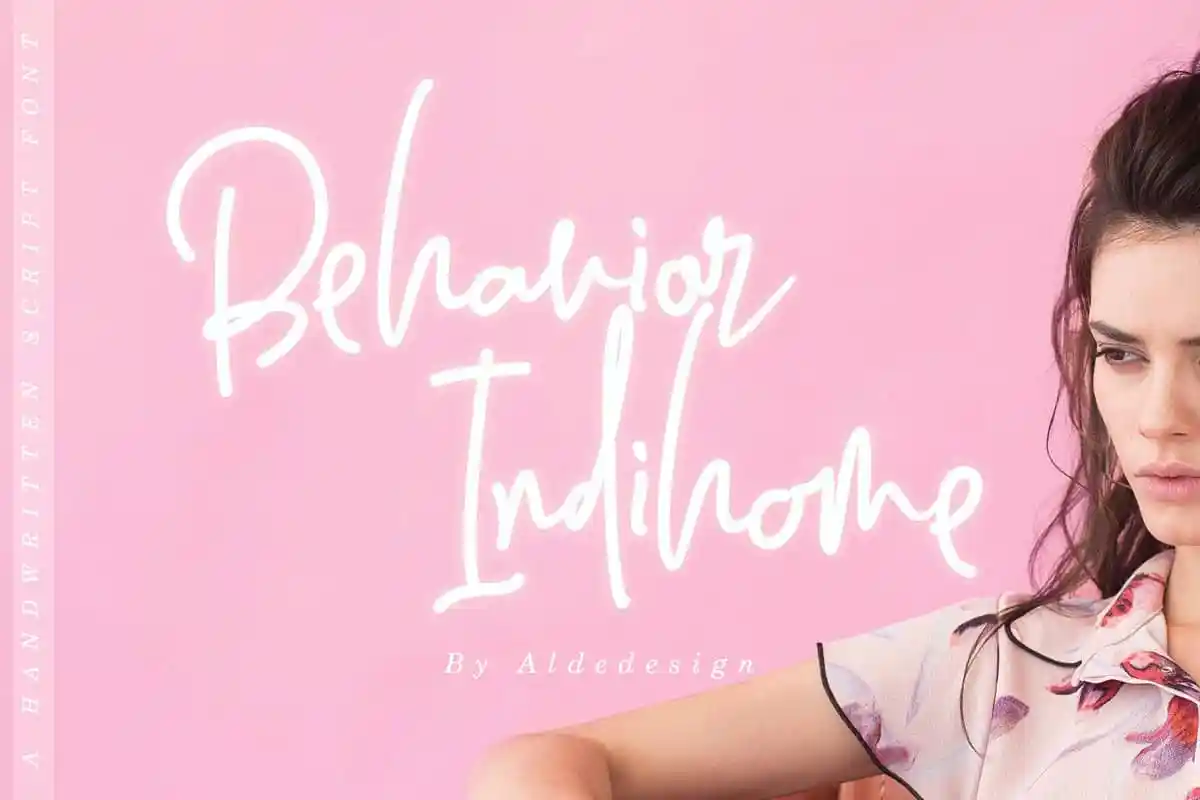
Behavior Indihome Signature Font – Fonte Grátis
Behavior Indihome Signature Font
Introduzimos a nova fonte Behavior Indihome Font criada pela 24Design. Esse é um tipo de graffiti feito à mão que traz uma mistura única e sofisticada, com ligaturas naturais. Essa fonte destaca-se por seu tom elegante, ao mesmo tempo leitorável e refinado. Seu estilo único faz dele um recurso visual irresistível. O resultado é uma fonte fácil de usar e extremamente versátil, perfeita para adicionar um toque de sofisticação à sua obra de design. Este é o tipo certo para quando você busca criar algo que seja ao mesmo tempo simplesmente perfeito e única em seu estilo.